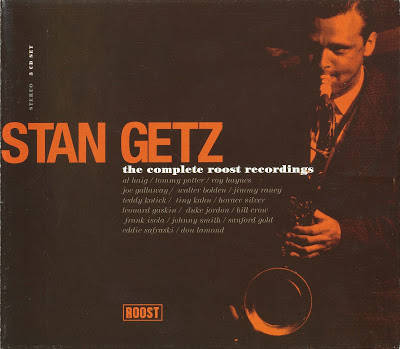
Typografie und Musik im Einklang
ich bin im Moment an einem Projekt um Typografie und Musik in Einklang zu bringen..
Ich habe bereits diverse Musikrichtungen udn Schriftstile/Schnitte visuell dargestellt um einen Einklang von Schrift und Charakter der Musik zu erreichen. Ich bin dabei unterschiedlich vorgegangen und habe es entweder auf das Musikstück, den Interpret, Komponist oder die Musikrichtung abgestimmt.
Im Moment bin ich dabei die Trade Gothic umzusetzen, bin mir aber noch nicht sicher welche Musikrichtung oder welcher Titel am besten passt.
Für mich ist die Trade Gothic geerdet und robust, seriös...
Mich würde interessieren, an welche Musikrichtungen oder welchen Sontitel denkt Ihr bei der Schrift?
Trade Gothic ist für mich typisch amerikanisch – ist vielleicht etwas verkopft, da ich das von der Klassifizierung herleite – und wurde 1948 entworfen. Ich würde entsprechende Musik dazu suchen. Da sie sehr schnörkellos ist fällt sowas wie Frank Sinatra z. B. weg, vielleicht eher Cool-Jazz a la Miles Davis oder Chet Baker  :-?
… oder Stan Getz, der geht schon eher Richtung Fahrstuhlmusik, das könnte passen  :hammer:
ich denke auch automatisch an typische amereikanische "lala" musik, hintergrundmusik in einem restaurant oder wie du sagtest fahrstuhl.
Könnte sie mir aufgrund ihrer schlichten, robusten aber auch warmen Ausstrahlung ebenso gut bei Folk/Acoustic vorstellen, also z.B. Mumford and Sons, The Lumineers, Jack Johnson, Josh Garrels … insbesondere die schmalen Schnitte.
Vielen Dank für die bisherigen Antworten und Eure persönliche Einschätzung und Einordnung. Es ist spannend zu sehen, wie die Schrift von verschiedenen Menschen, verschiedenen Musikern oder Musikrichtungen zugeordnet wird aber doch im Querschnitt alles in eine Richtung geht...
Die Trade Gothic hat auch was von der nüchternen Sachlichkeit von Paul Hindemith
Spannend! An Hindemith hätte ich zunächst überhaupt nicht gedacht. Mir persönlich kam als erstes in den Sinn daß es nach der Erhöhung der Komplexität (Expressionismus, Zwölftonmusik) wieder zu einer starken Vereinfachung gekommen ist. In diesem Sinn hätte ich Henryk Górecki oder Philip Glass vorgeschlagen. Hindemith ist eine ganz andere Richtung, die mir gut gefällt. Trotzdem finde ich daß Jazz es nach wie vor am besten trifft.